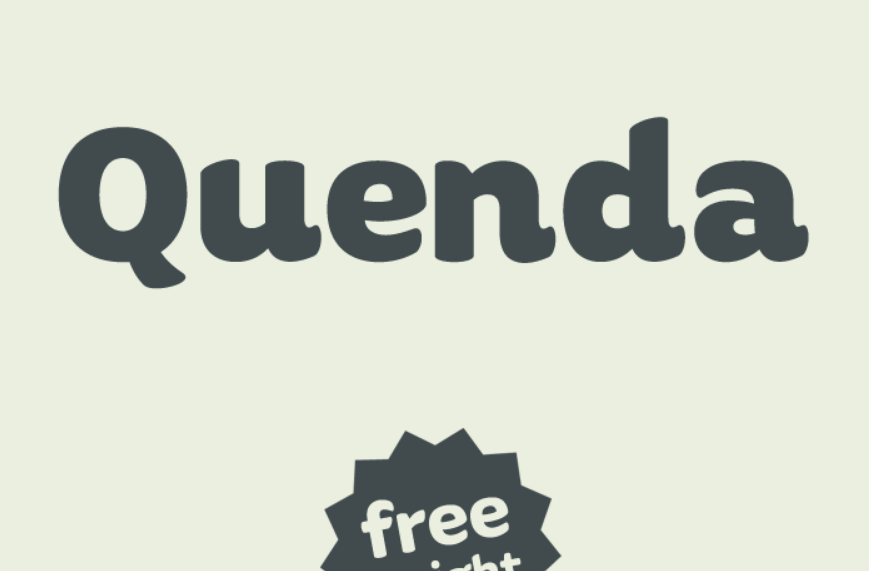
Quenda é uma família de tipo sans-serif composta por seis pesos: fino até grosso. O que destaca Quenda são seus terminais redondos e uma aparência levemente escrita à mão, conferindo-lhe um ar descontraído e aconchegante. Este fator faz do Quenda o ideal para projetos de marketing e marca. Sua simplicidade e facilidade na leitura complementam perfeitamente os objetivos estéticos dos criadores de conteúdo online e designers gráficos, oferecendo uma fonte elegante que se destaca em designs digitais. Além disso, seu contraste entre os diferentes pesos é notável, permitindo que o designer escolha a melhor opção para qualquer projeto, do texto fino até um grosso forte. Quenda não apenas enriquece a aparência de qualquer projeto gráfico, mas também contribui para a experiência visual em uma maneira mais envolvente e natural, tornando-a uma fonte ideal tanto para iniciantes quanto para profissionais da design.